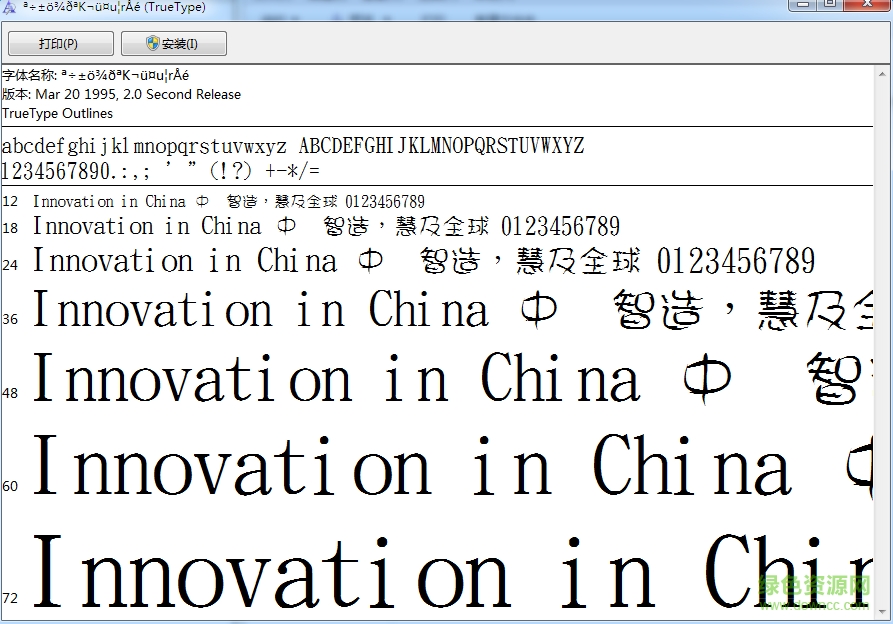
金梅樹枝美工是一款個(gè)性鮮明的電腦字體,是專為需要用到各種不同字體的美工行業(yè)所設(shè)計(jì),字體整體效果非常統(tǒng)一,讓你在進(jìn)行美工作品設(shè)計(jì)時(shí)能夠?qū)⒄w效果做的更加出色,適用的范圍也餓非常的廣泛,有需要的朋友歡迎來綠色資源網(wǎng)下載!
金梅樹枝美工字體是一款用于美工設(shè)計(jì)方面的字體,該字體結(jié)構(gòu)嚴(yán)謹(jǐn)而疏爽,情態(tài)變化多端,風(fēng)度超逸,墨采飛動,精麗妍美而又自然流便,看上去十分美觀!